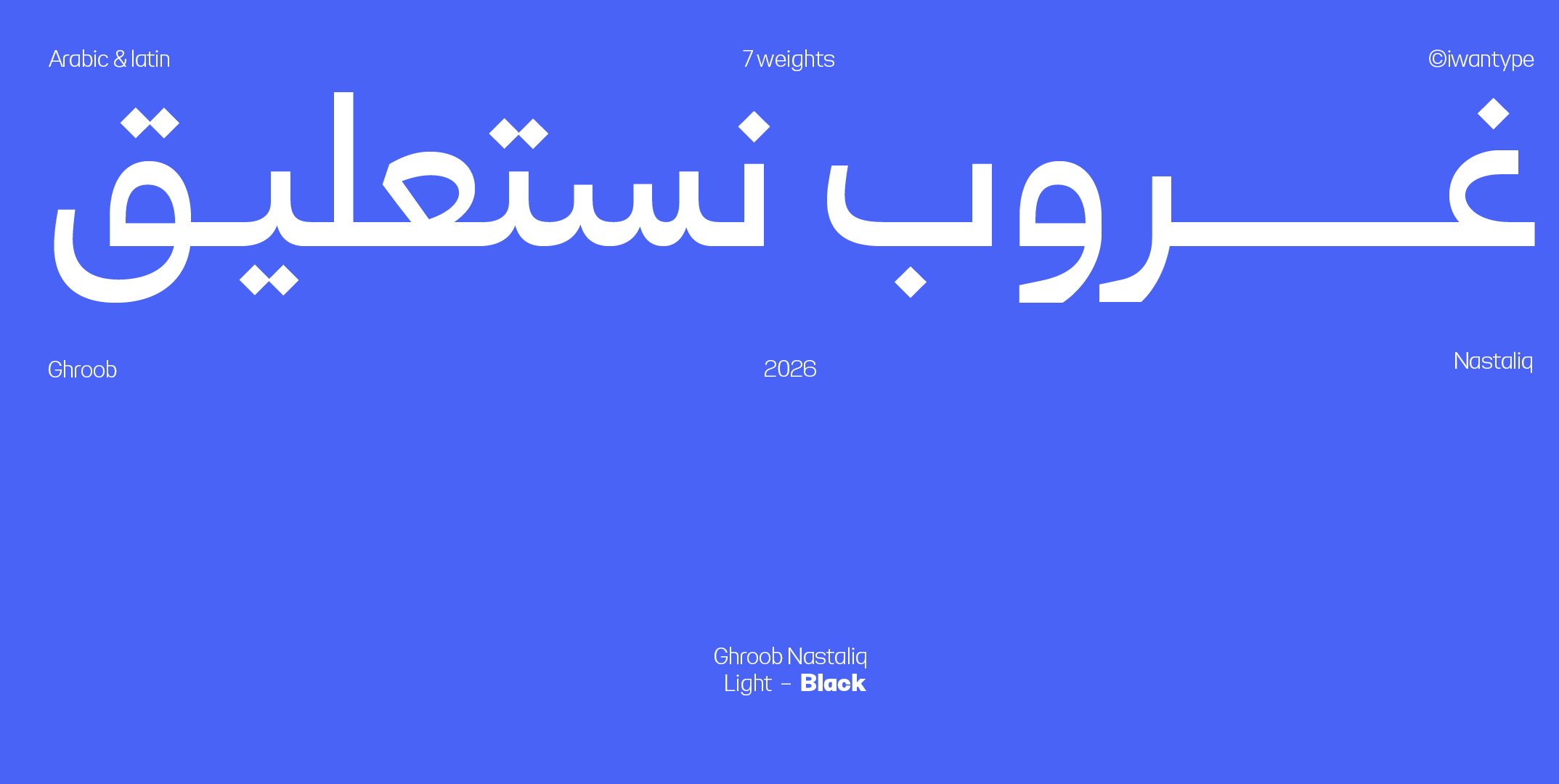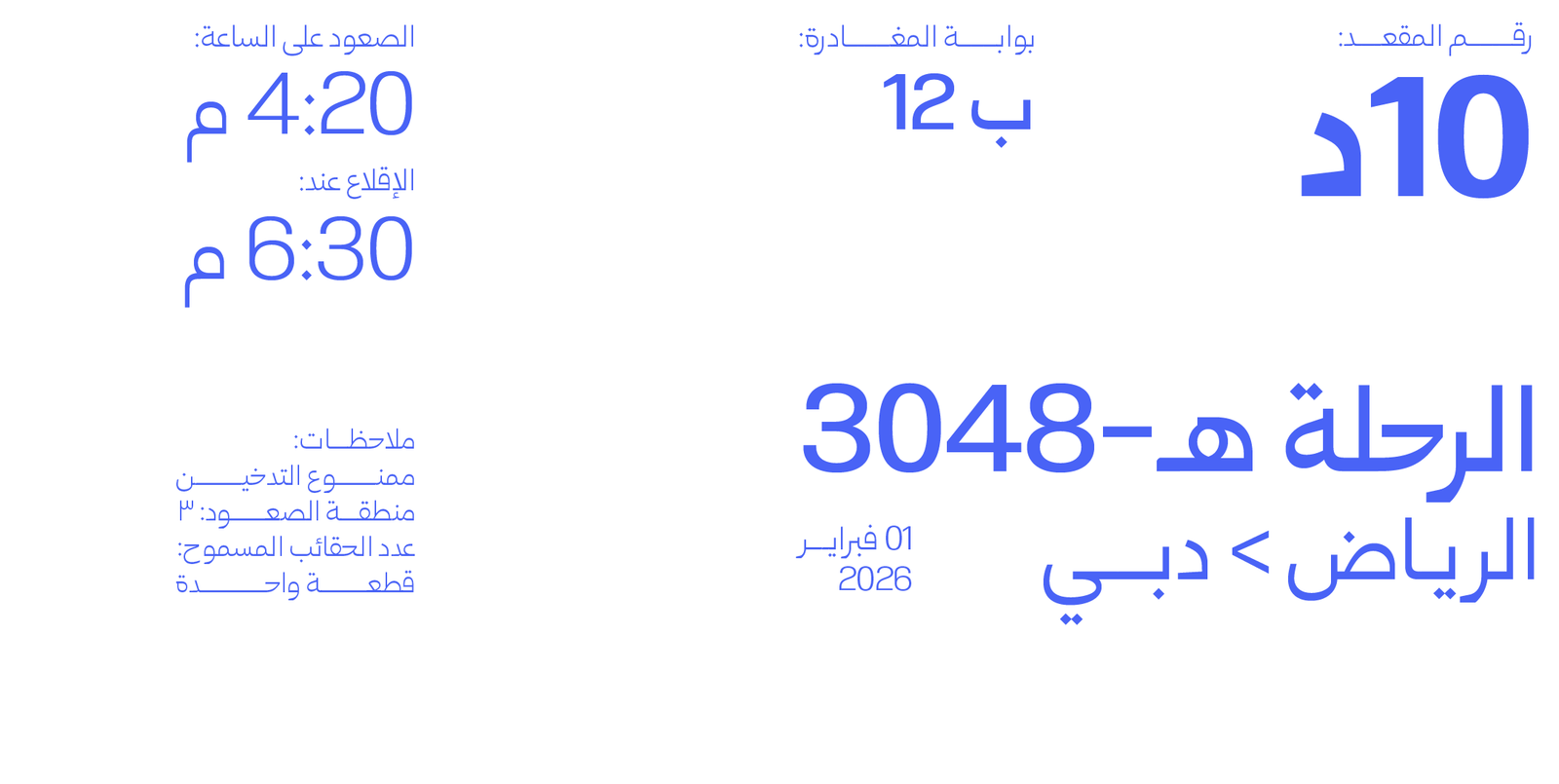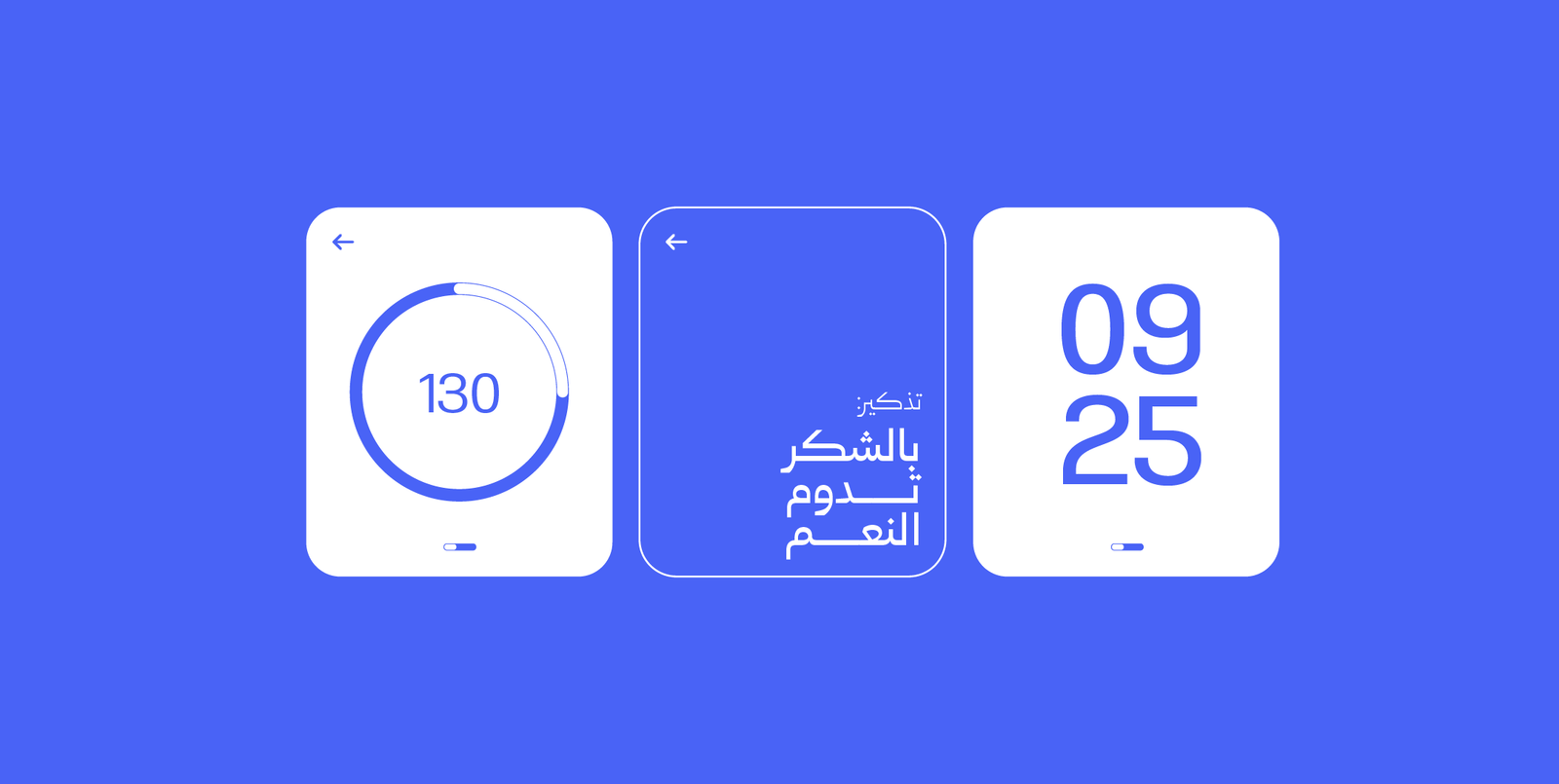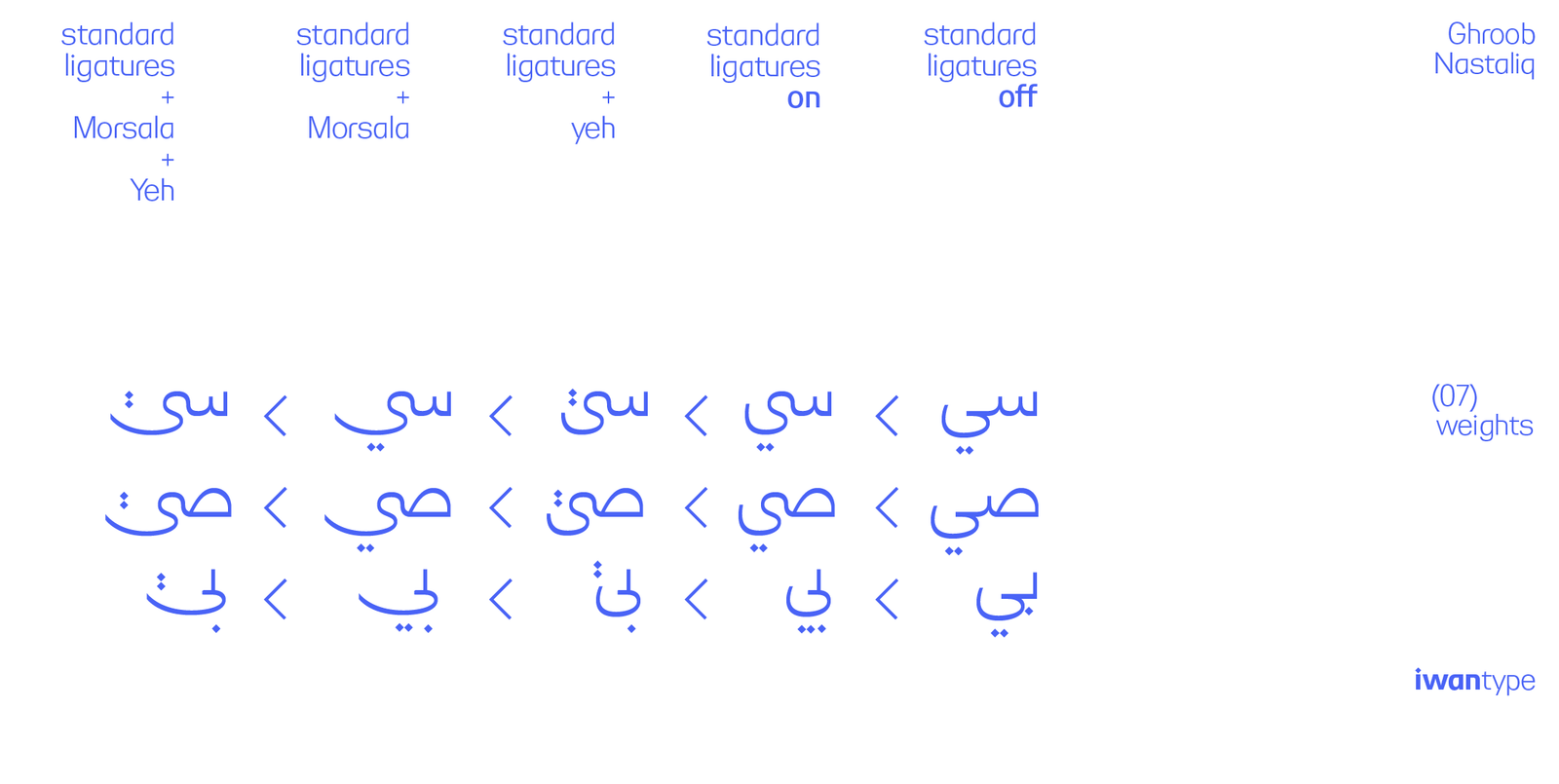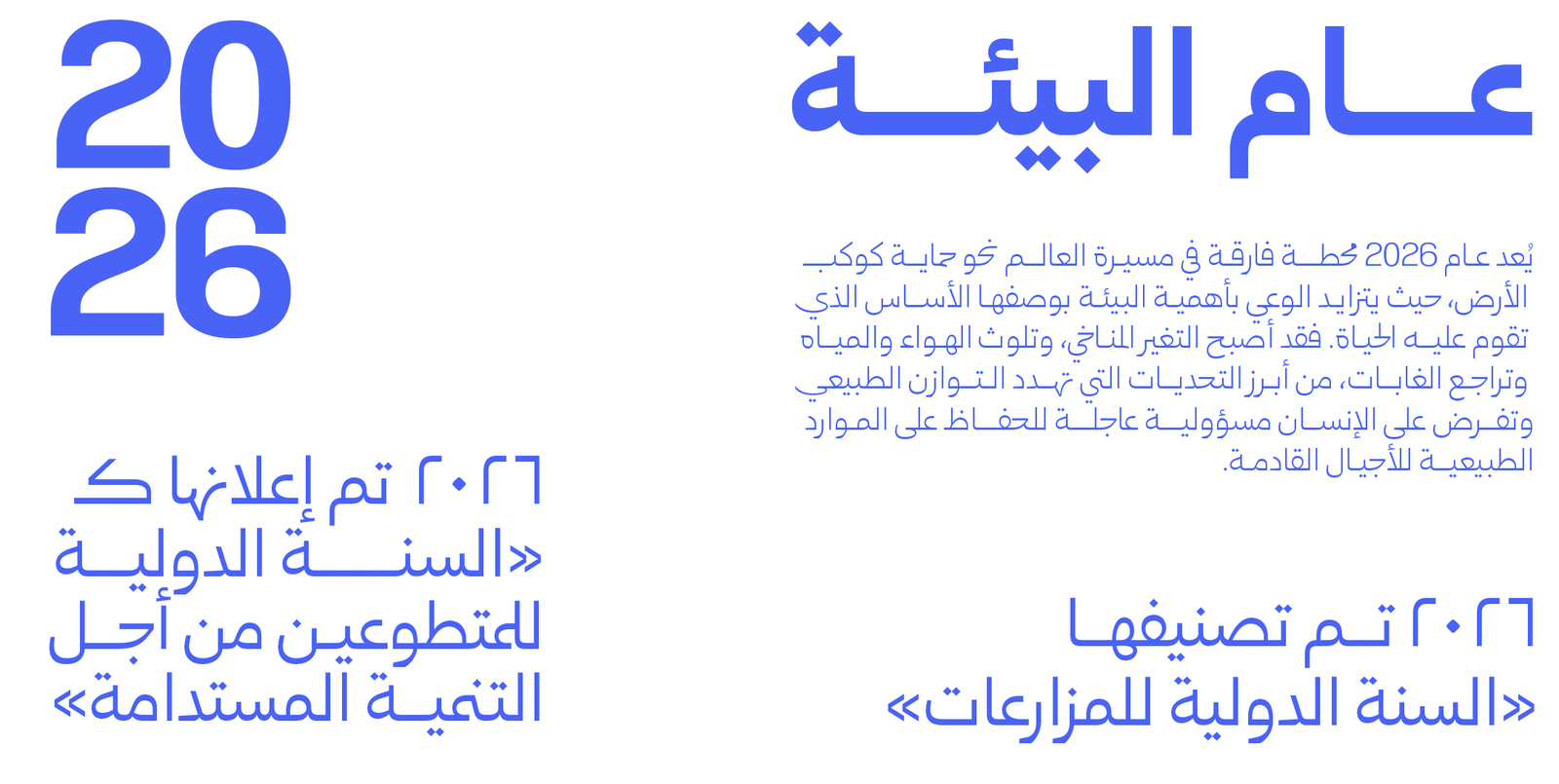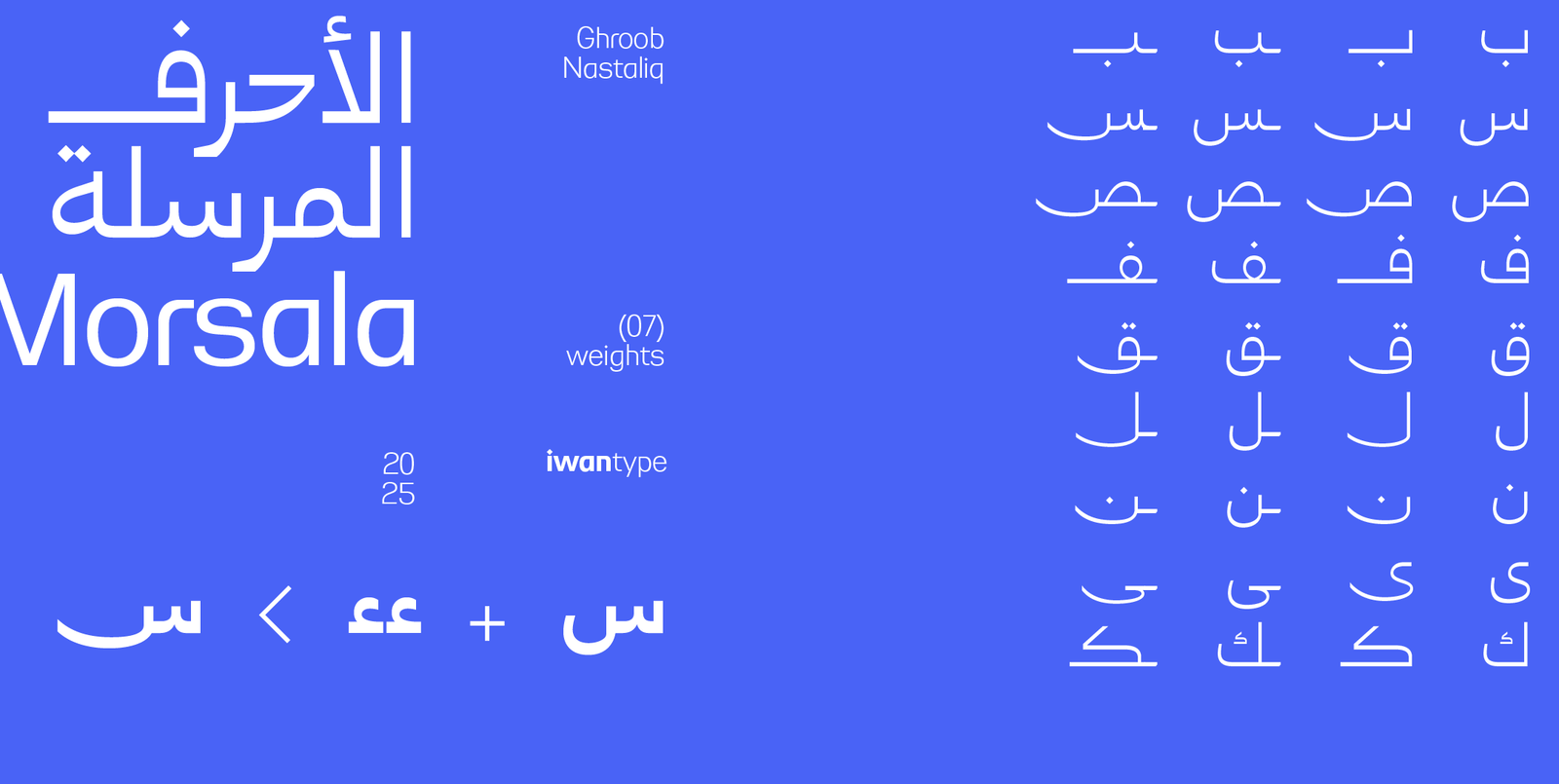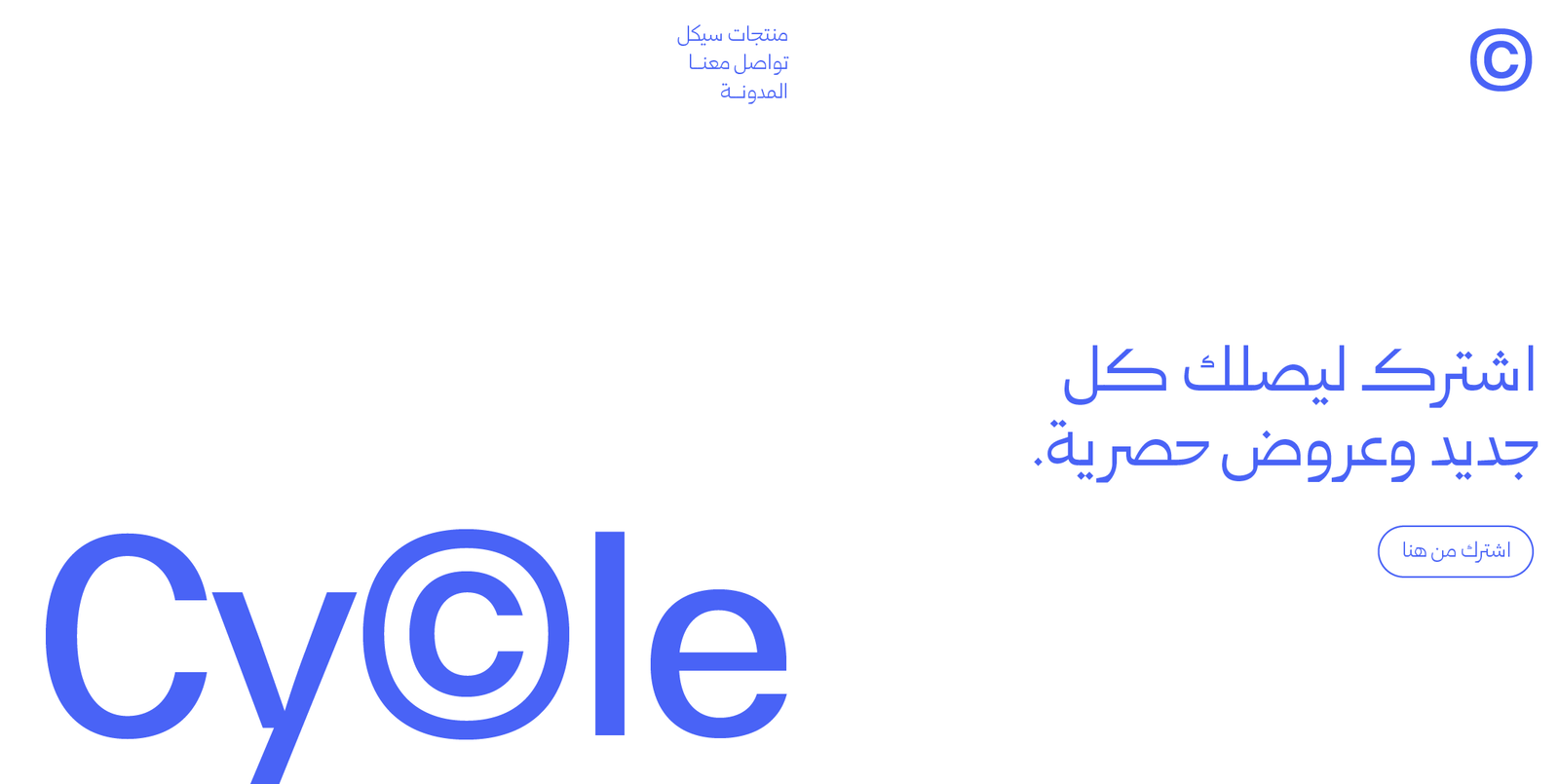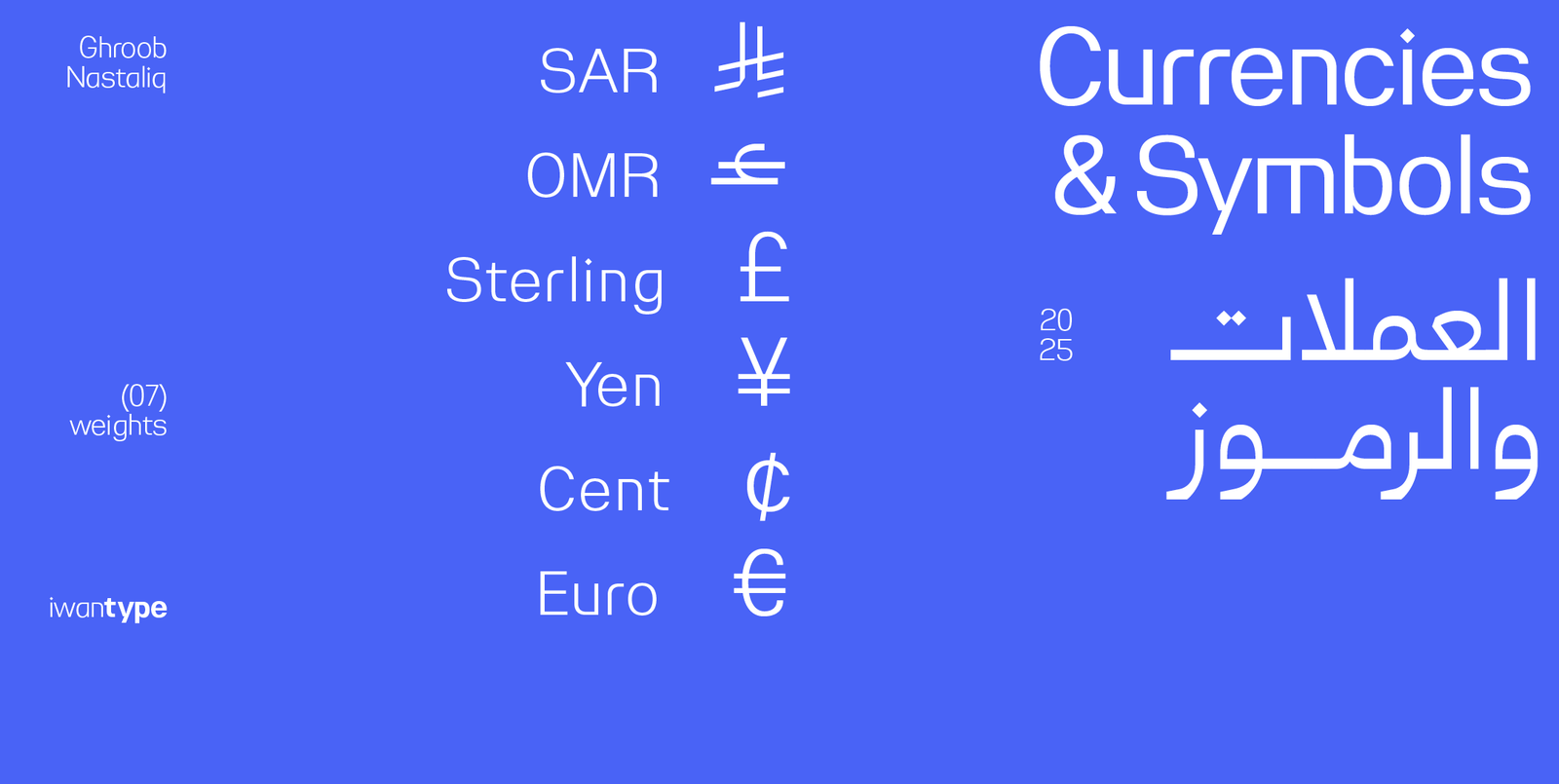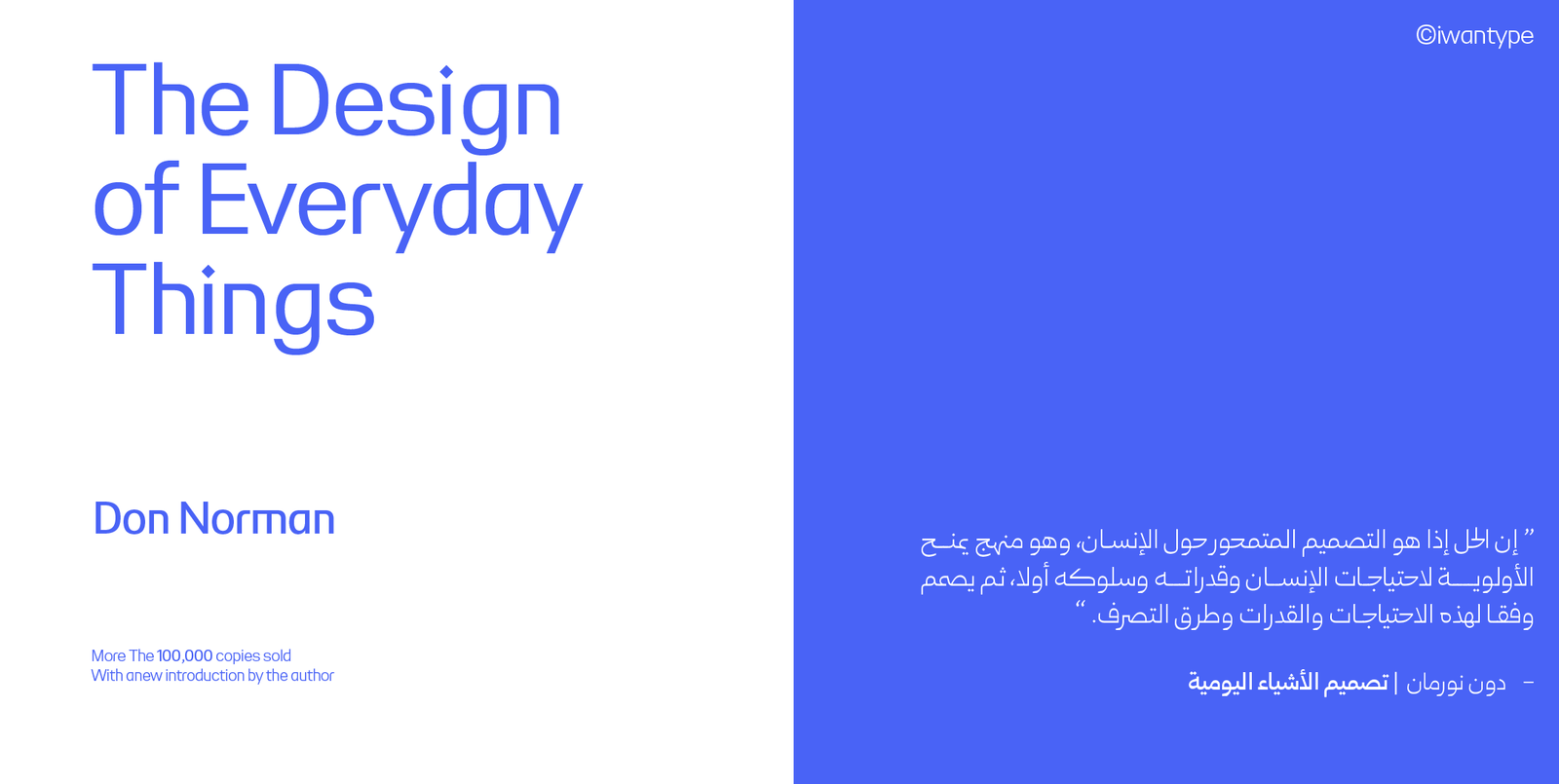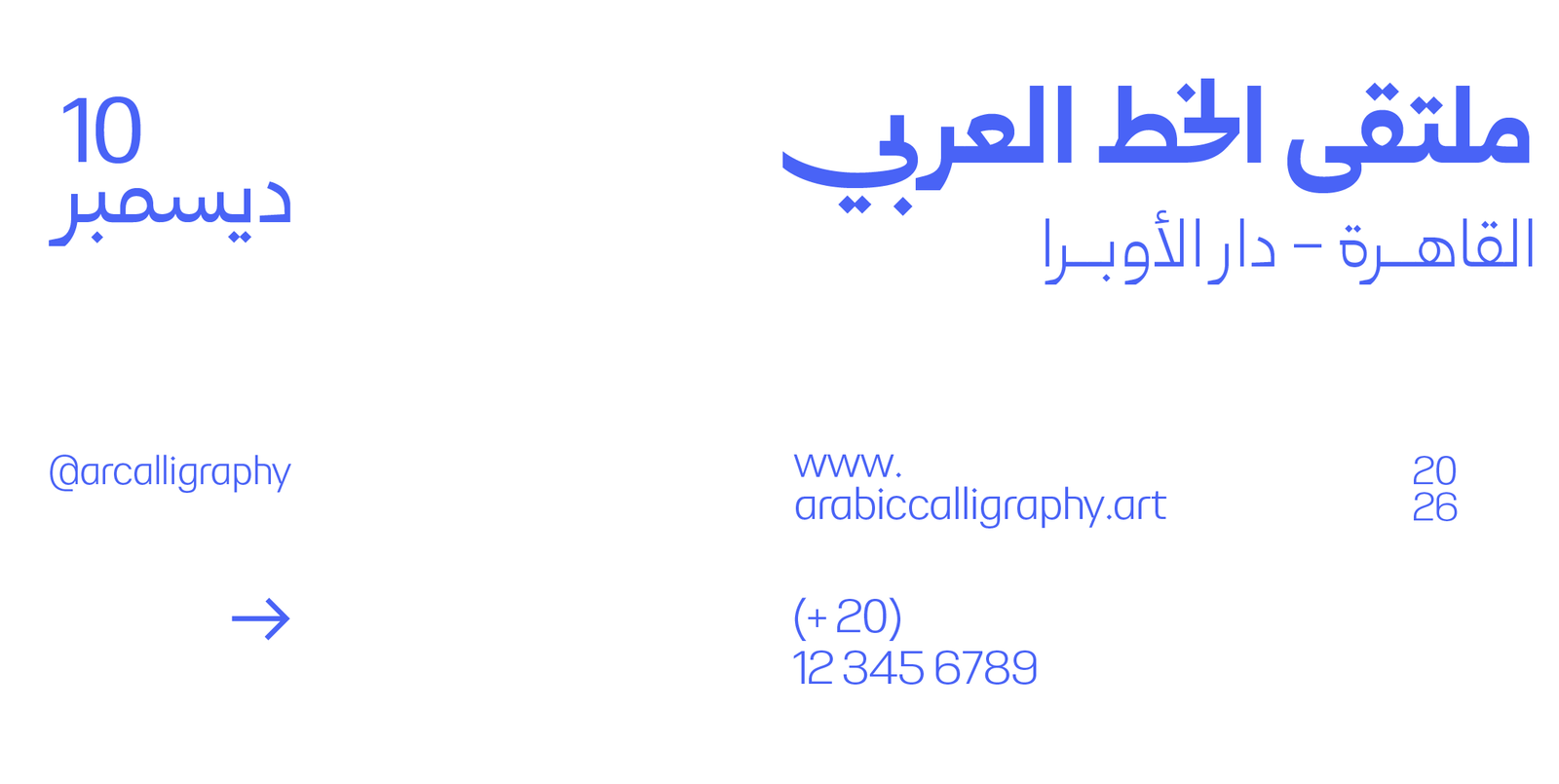
غروب نستعليق – Ghroob Nastaliq Typeface – خط نسخ ونستعليق
غروب نستعليق هو إصدار مشتق من عائلة خط غروب، يقدّم معالجة معاصرة تجمع بين بنية النسخ وروح النستعليق، مع توجّه هندسي واضح وتبسيط بصري يمنح الخط شخصية هادئة، متزنة، وسهلة الاستخدام في مختلف السياقات التصميمية.
في هذا الإصدار، أُعيدت صياغة النستعليق بأسلوب أكثر انتظامًا وانضباطًا، يخفّف من تعقيده التقليدي دون أن يفقد حسّه التعبيري، بينما توفّر البنية النسخية قاعدة مستقرة للقراءة والانسياب الطباعي، ليشكّل الخط مساحة توازن بين التعبير والجودة الوظيفية.
مميزات غروب نستعليق:
يتضمن الخط العديد من مزايا OpenType التي تضفي عليه مرونة وتنوعًا في الاستخدام، مثل:
- أحرف مرسلة (تُفعَّل بإضافة “ءء” بعد الحرف)
- حرف ياء بنزول أقل: يقلل من نزول السطر ويعزّز انتظام النصوص.
- أحرف مركّبة تُحسّن سلاسة التراكيب وتناسق النص.
- سبعة أوزان كاملة تمنح مرونة واسعة في الاستخدام الطباعي.
- يدعم رمز الريال السعودي والريال العُماني ،ويتم تفعيلهما تلقائيًا عند كتابة الاختصارات: ر.س للريال السعودي ر.ع للريال العُماني
اللغات: العربية، اللاتينية، والكردية
الأوزان: ٧ أوزان